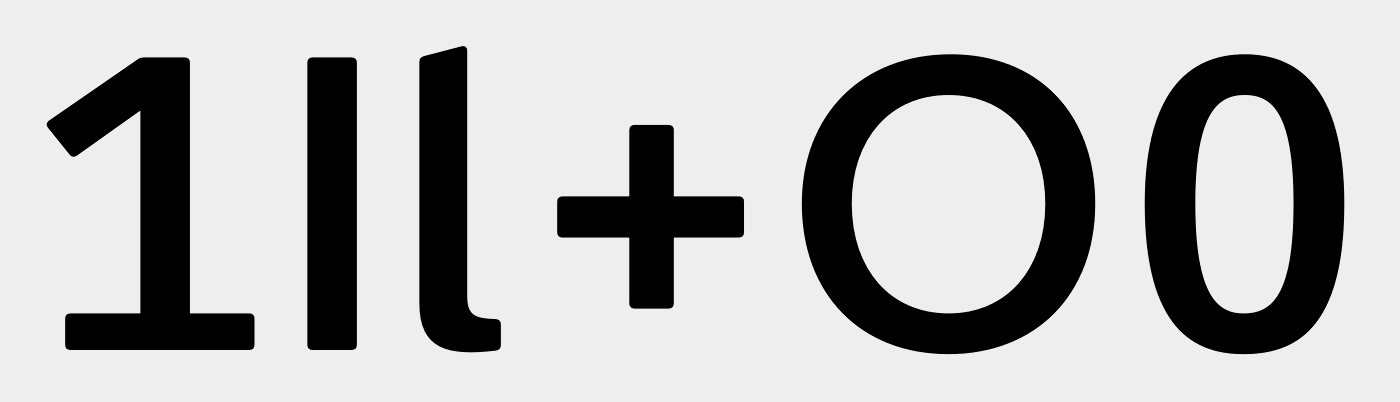
Signaletik, Schrift, Differenzierung
ich arbeite gerade an einem Orientierungssystem, es ist meines erstes Projekt in dieser Richtung. Es handelt sich um ein mäßig komplexes Projekt.
Die Hausschrift ist die FF Meta. Dort unterscheiden sich z.B. o und 0 überhaut nicht. Das O auch nur durch Größe. Diese Buchstaben lassen sich also nicht eindeutig differenzieren. Insofern ist diese Schrift eher ungeeignet oder?
Nun dachte ich, vielleicht wäre ja die FF Info eine passende Ergänzung, da auch von Spiekermann.
"Die FF Info besticht durch ihre klare Formensprache und gute Leserlichkeit. Kritische Buchstabenpaare sind möglichst unmissverständlich gestaltet."
Nun bin ich etwas verwundert, da die Differenzierung der oben genannten Buchstaben auch nicht das Gelbe vom Ei ist. Sie findet auch nur durch die Größe statt, nicht aber durch die Form. Diese Schrift wurde aber ja zweckgebunden entwickelt. Nun stellt sich mir die Frage, wie dieser Differenzierungsaspekt überhaupt zu werten ist.
Wie seht ihr das? Reicht eine Differenzierung durch die Größenunterschiede aus oder ist das tatsächlich ein Mangel der FF Info? Für ein hochkomplexes System, wie einen Flughafen, tut sie es aber ja anscheinend schon ganz gut.
Wenn O und 0 wirklich unmissverständlich sein sollen, ist das gegebenenfalls auch als OpenType-Feature »Slashed Zero« gezielt ansprechbar. Denn nicht immer ist der Effekt ja überhaupt gewünscht. Solche Schriften haben ja ein breiteres Einsatzspektrum und die maximale Unterscheidbarkeit bestimmter Zeichen steht dann gar nicht unbedingt an oberster Stelle.